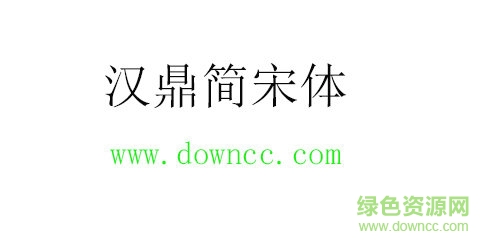
漢鼎簡宋體字體是一款宋體字體,可以用于廣告設(shè)計(jì)、海報(bào)設(shè)計(jì)等方面,是從事廣告設(shè)計(jì)工作等人員電腦中所必備的一款字體,它能重點(diǎn)突出你的廣告信息內(nèi)容,非常的實(shí)用又方便,有需要的朋友快來綠色資源網(wǎng)免費(fèi)下載哦!